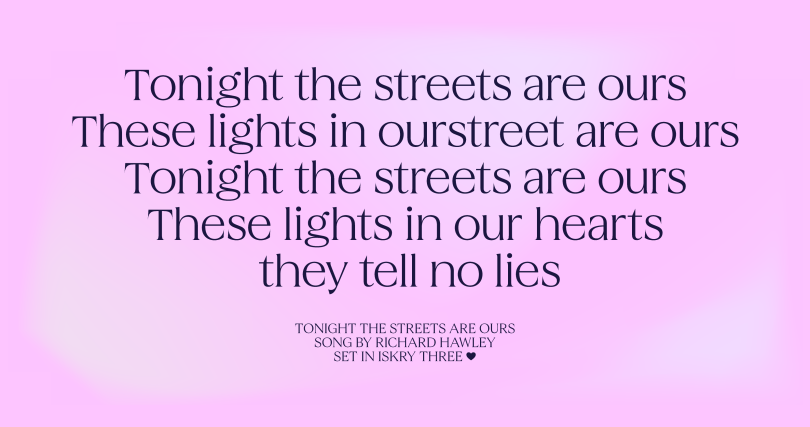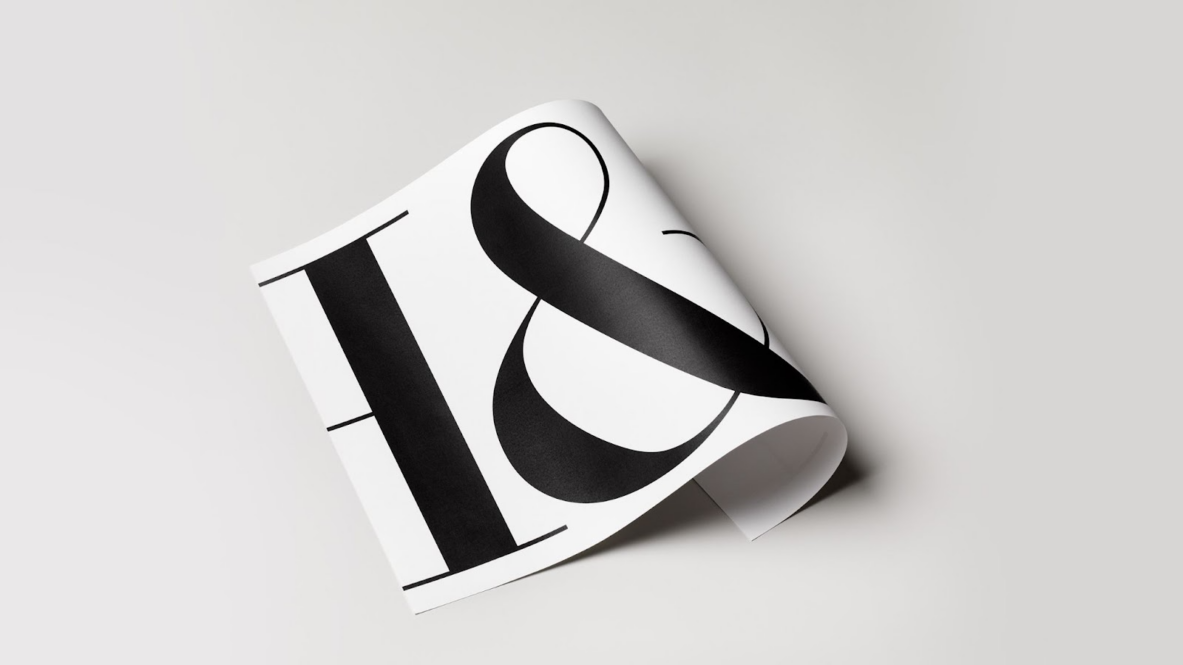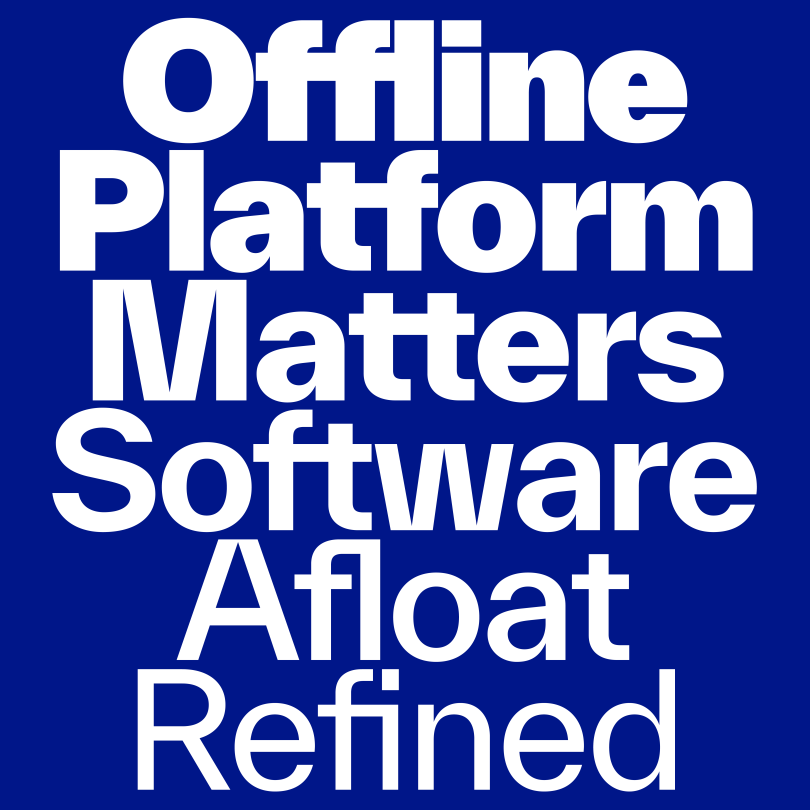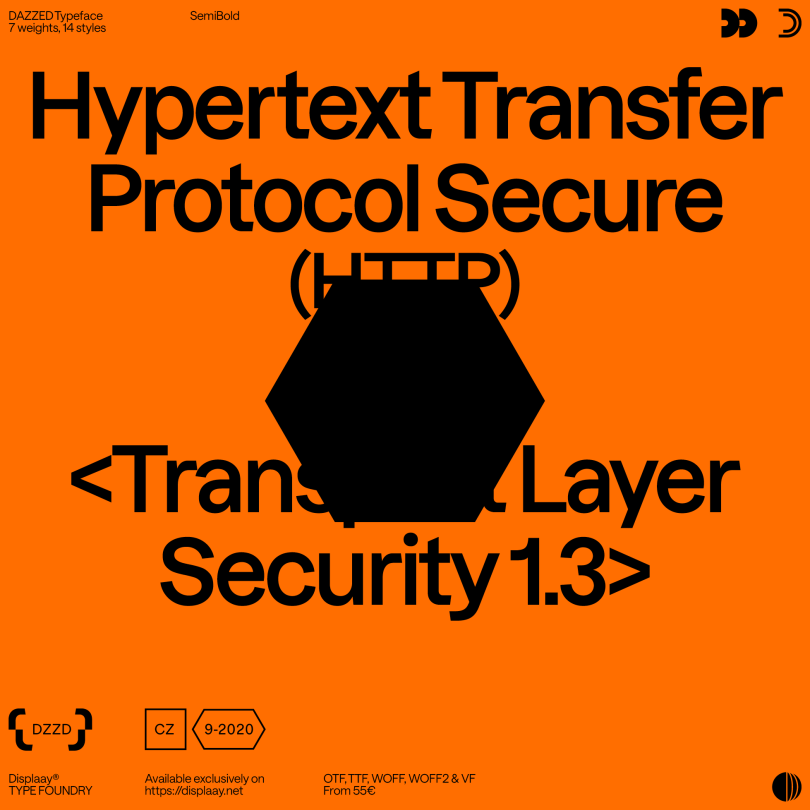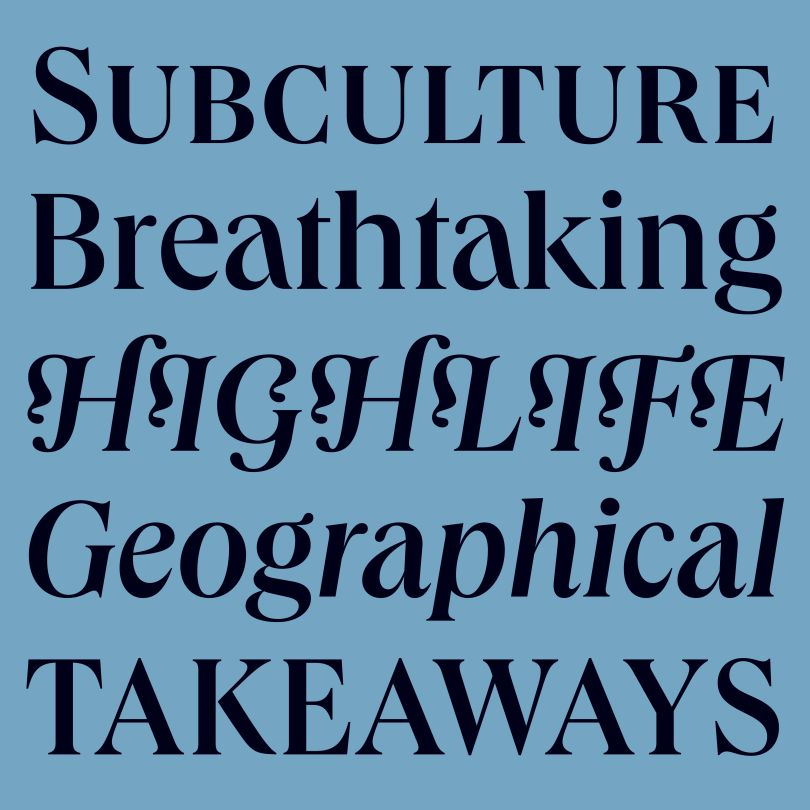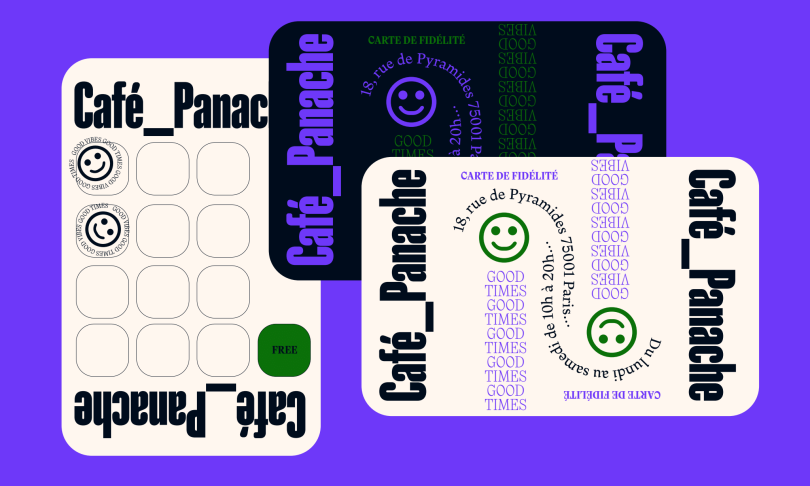
Lựa chọn font chữ thiết kế cho dự án vừa như niềm vui, vừa như nỗi ám ảnh lớn của mỗi Designer. Làm sao để cân bằng yếu tố thương mại và font cách cá nhân luôn là dấu hỏi khó tìm lời giải. Trong bài viết dưới đây, hãy cùng Arena Multimedia khám phá 14 gợi ý kiểu chữ giúp Designer giải tỏa nỗi lo này nhé!
Tương tự tình yêu, cảm xúc của nhà thiết kế dành cho các font chữ đôi lúc thoáng qua, nhẹ nhàng nhưng cũng đầy mãnh liệt và đam mê. Mặt khác, mỗi Designer đều mong muốn trải qua năm tháng ổn định cùng một kiểu chữ chắc chắn, đáng tin cậy, có thể hỗ trợ và đồng hành xuyên suốt các dự án trong khoảng thời gian theo đuổi thiết kế.
14 font chữ thiết kế đáp ứng mọi “jobs” của Designer (Phần 1)
Dưới đây là danh sách 14 font chữ thiết kế giúp Designer tạo nên sự kết hợp hoàn hảo cho đời sống thiết kế của riêng mình, đáp ứng mọi cung bậc cảm xúc và mục đích cụ thể của nhà thiết kế. Tất nhiên, giữa vô vàn kiểu chữ sẽ không tránh khỏi lựa chọn chủ quan, nhưng dù bạn không thật sự yêu thích thì đây vẫn là những kiểu chữ được phát triển bởi đội ngũ studio và Designer xuất sắc từ khắp nơi trên thế giới, rất đáng để bạn cân nhắc.
1. Irregardless của Ohno Type
Irregardless là kiểu chữ sans-serif do James Edmondson của công ty Ohno Type thiết kế, sở hữu giao diện tươi mới, dễ nhìn và vô cùng độc đáo. Về quá trình ra đời của kiểu chữ này, chính James cũng cảm thấy mơ hồ: “Một vài dự án có con đường phát triển rõ ràng nhưng Irregardless thì hoàn toàn trái ngược. Tôi không biết ý tưởng về kiểu chữ bắt nguồn từ đâu, và trong phần lớn thời gian nghiên cứu về Irregardless, tôi vẫn không chắc chắn dự án sẽ tiến triển đến đâu. Đây giống như một sự rèn luyện để tôi chống lại sự bốc đồng của bản thân, xây dựng thói quen để có thể sáng tạo những điều mới mẻ và không thoải mái.”
Được phát hành vào tháng 5/2021, font chữ thiết kế này là một trong số nhiều kiểu chữ vui nhộn và mang tính nguyên bản của Ohno Type mà James đã ra mắt vào năm 2018. Cùng với việc sáng tạo font chữ, công ty cam kết đưa Ohno trở thành một cái tên ảnh hưởng tích cực trong cộng đồng Graphic Design và Typography Design. Để thực hiện hóa mục tiêu này, họ sẽ tiến hành những buổi đối thoại, chia sẻ cùng sinh viên, hoặc đưa ra lời nhận xét, góp ý và các nội dung giáo dục miễn phí.
2. NaN Tragedy của NaN
NaN Tragedy là một font chữ gốc được tạo ra bởi JB Morizot từ NaN theo định dạng văn bản, chữ nghiêng và kiểu chữ hiển thị. Cấu trúc và nguồn năng lượng NaN Tragedy của hướng đến sự đối lập cùng tồn tại bên trong một thực thể: “Cổ điển nhưng vẫn mang tính đương đại. Độc đáo nhưng vẫn có tính tiện dụng. Năng động, font khoáng nhưng vẫn chắc chắn. Lộng lẫy nhưng rõ ràng và đơn giản.”
NaN Tragedy Text kết hợp các chức năng của kiểu chữ văn bản với hình dáng độc đáo, sử dụng hiệu chỉnh quang học để hiện thị tính năng. Chẳng hạn như font cách hướng nghiêng của ký tự và độ tương phản dày mỏng từ kiểu chữ thư pháp. Trong khi đó, thiết kế của font chữ NaN Tragedy Display mang tính nhỏ gọn và chặt chẽ hơn, góp phần nhấn mạnh sự đặc sắc cho những dòng thiết kế tiêu đề.
Phát hành lần đầu tiên vào năm 2019, đây là một trong nhiều kiểu chữ tuyệt vời được thiết kế bởi NaN, studio chuyên về Graphic Design và Typeface Design tại Berlin và Sydney. Đội ngũ studio cho biết: “Cùng hệ thống cộng tác viên, đội nhóm và khách hàng tuyệt vời của chúng tôi, chúng tôi khám phá tất cả mối liên quan giữa code và công nghệ nhằm phục vụ cho các mục đích cụ thể của từng dự án.”
3. Everett của TYPE.WELTKERN
Everett là một kiểu chữ sans-serif sở hữu thiết kế tối giản. Cấu trúc đối xứng của Everett được tạo nên bởi sự kết hợp giữa nét vẽ truyền thống và các yếu tố kỹ thuật. Những chi tiết mạnh mẽ trong kiểu chữ tạo nên tính tập trung cao độ nhưng vẫn đảm bảo sự thoải mái cho việc đọc, cân bằng hài hòa bởi tính đồ họa và mục tiêu gây sự chú ý, thu hút đối với người xem.
Sự phối hợp giữa ascenders (phần chữ nằm trên đường cơ sở) và descender (đoạn kéo dài bên dưới đường cơ sở) cho phép người thiết kế sắp đặt văn bản với khoảng cách dòng chặt chẽ, tiết kiệm không gian. Các font chữ được trang bị những phong cách khác nhau, bao gồm cả chữ ghép, phân biệt chữ hoa và chữ thường cùng nhiều tính năng hơn nữa. Sự thay đổi độ dày mỏng từ Hairline đến Super với chữ in nghiêng tương ứng, tạo thành tính nhất quán và linh hoạt, phù hợp là font chữ thiết kế dành cho thiết kế sách, poster, bộ nhận diện thương hiệu, hệ thống biển báo, v.v…
Ban đầu, kiểu chữ Everett xuất hiện từ năm 2015, khi Nolan Paparelli vẫn còn trong quá trình học tập tại ECAL (Đại học Nghệ thuật và Thiết kế Lausanne, Thụy Sĩ). Theo đó, Nolan được truyền cảm hứng từ tác phẩm của nhiép ảnh gia người Mỹ – Daniel Everett. Khi Nolan phát triển kiểu chữ này, nó nhanh chóng in đậm dấu ấn cá nhân và trở thành phong cách riêng của nhà thiết kế với thể loại nghệ thuật bí ẩn, kỳ lạ (Grotesque).
Everett chính thức xuất xưởng vào tháng 3/2021, là một trong những kiểu chữ cao cấp do TYPE.WELTKERN, công ty thiết kế kiểu chữ của Thụy Sĩ thành lập vào năm 2021 bởi Nizar Kazan. Mục tiêu chính của TYPE.WELTKERN hướng đến việc tôn vinh đội ngũ nhà sáng tạo làm ra các kiểu chữ, chia sẻ doanh thu từ đối tượng, sách hoặc font chữ thiết kế mà họ sản xuất và xuất bản. Công ty tự hào rằng nhà thiết kế của họ đạt được phần trăm doanh số tốt hơn so với mức trung bình thị trường.
4. Font chữ thiết kế Rainer của Vectro Type
Rainer thuộc kiểu chữ sans-serif hình học, sở hữu kiểu dáng thời thượng và hiện đại, phù hợp cho những tiêu đề chặt chẽ hoặc bất cứ đối tượng nào cần đến định dạng big type để tạo điểm nhấn và gợi tâm trạng cho người xem. Rainer được nén với khẩu độ đón, chiều cao font chữ khá lớn, phần ascenders (chữ nằm trên đường cơ sở) ngắn và descender (đoạn kéo dài bên dưới đường cơ sở) còn ngắn hơn. Rainer bao gồm 12 font cách cùng 6 mức độ đậm nhạt khác nhau (từ Hairline đến Bold) ở dạng thẳng, nghiêng và đi kèm một số hỗ trợ ngôn ngữ mở rộng, cũng như tất cả thể loại hình dạng mũi tên và ký tự được chọn lựa một cách cẩn thận.
14 font chữ thiết kế đáp ứng mọi “jobs” của Designer (Phần 1)
Ảnh: creativeboom.com
Font chữ thiết kế Rainer do Philipp Neumeyer thiết kế và được phát hành bởi Vectro Type – studio lĩnh vực Typeface Design có trụ sở tại thành phố Portland, tiểu bang Oregon, Hoa Kỳ, chuyên thiết kế kiểu chữ theo yêu cầu, các dịch vụ sản xuất font chữ, v.v… Thành lập vào năm 2015 bởi bộ đôi Travis Kochel và Lizy Gershenzon, studio nổi tiếng với việc khám phá điểm giao thoa giữa công nghệ, sự hữu ích và nét vui tươi trong thiết kế kiểu chữ.
5. Iskry của Laic
Iskry là kiểu chữ serif với những ký tự độc đáo và kỳ quặc, chứa đựng sự tương phản mạnh mẽ, sắc nét và rực rỡ, vô cùng thích hợp cho mục đích hiển thị trên màn hình hoặc sử dụng trong các ấn phẩm in ấn. Trục chữ cái của kiểu chữ vô cùng đa dạng kết hợp cùng chiều lớn, phù hợp để ứng dụng cho thiết kế tiêu đề.
14 font chữ thiết kế đáp ứng mọi “jobs” của Designer (Phần 1)
Ảnh: creativeboom.com
Font chữ thiết kế Iskry ra đời vào tháng 1/2020 bởi Laic – một studio thiết kế đồ họa có trụ sở tại Warsaw, Ba Lan chuyên về thiết kế kiểu chữ và các tác phẩm nghệ thuật bằng con chữ. “Iskry” trong tiếng Ba Lan có nghĩa là “tia lửa”, studio giải thích: “Tia lửa là thứ gì đó rất nhỏ, có thể đột ngột phát ra một sự ấm áp hoặc ánh sáng nhưng cũng có thể là những mảnh nhỏ của chất liệu phát sáng.”
6. Queen của Kilotype
Queen được xuất bản lần đầu tiên vào năm 2019, là một kiểu chữ hiển thị với lối thiết kế cổ điển và thanh lịch, lấy cảm hứng từ thiết kế của Bodonis & Didots. Tuy nhiên, điểm khác biệt của Queen nằm ở việc lược bỏ những cấu trúc có phần cứng nhắc và tập trung hướng đến sự tươi vui trong thiết kế. Font chữ thiết kế Queen nhận được nhiều điểm cộng nhờ việc tích hợp một loạt tính năng và sự phức tạp của kiểu chữ.
14 font chữ thiết kế đáp ứng mọi “jobs” của Designer (Phần 1)
Ảnh: creativeboom.com
Queen sở hữu 3 độ rộng (Compressed, Condensed và Standard), được thiết kế với ý tưởng chủ đạo về sự đa dạng và kỳ quặc, đồng thời những tiêu chuẩn liên quan đến nhịp điệu trong thiết kế cần phá vỡ để có thể phát triển hơn nữa. Kiểu chữ thống nhất chữ “a” sẽ nghiêng về phía sau với các hướng nhấn nét xen kẽ của chữ “e” và “o”. Trong khi đó, chữ “t” nằm trên đường cơ sở, hoán đổi phần đuôi truyền thống bằng một kiểu chữ có chân. Đồng thời, các phần loe ra bên ngoài cũng được gọt giũa, tạo thành chữ “f” in nghiêng tương phản với phần cuối tương tự hình giọt nước.
Queen được sáng tạo bởi Kilotype – một xưởng đúc chữ của Đức thành lập vào năm 2017, hứa hẹn hỗ trợ nhiều ngôn ngữ cũng như sở hữu tiêu chuẩn sản xuất chất lượng cao đối với mọi kiểu chữ. Bên cạnh hệ thống danh mục kiểu chữ của riêng họ, Kilotype còn phát triển giải pháp tùy chỉnh dành cho khách hàng thương mại và các tổ chức.
7. Font chữ thiết kế Dazzed của Displaay
Dazzed là một kiểu chữ sans-serif tỷ lệ hẹp và được sử dụng đầu tiên cho mục đích điện ảnh, dung hợp một số phong cách trong một font chữ. Phát hành lần đầu vào tháng 7/2019, kiểu chữ gợi lên sự hài hước, kỳ quặc và kịch tích, thể hiện qua các chữ “a”, “e”, “c” và “g”. Đồng thời, Dazzed còn mang đến cảm giác hành động, khoa học viễn tưởng trong thiết kế của chữ “t”, “f”, “r”. Đặc biệt, phần đầu cuối bị cắt bỏ một phần, tương phản với những dạng chữ cổ điển khác. Các dấu chấm được thiết kế theo dạng hình tròn, giúp người đọc dễ dàng nhận dạng hơn, cũng như hệ thống chữ in nghiêng 18° với các mức độ thấp hơn vẫn có sẵn theo yêu cầu.
14 font chữ thiết kế đáp ứng mọi “jobs” của Designer (Phần 1)
Ảnh: creativeboom.com
Dazzed do studio Displaay phát triển, đây là địa chỉ chuyên về thiết kế đồ họa và thiết kế kiểu chữ, được thành lập vào năm 2016 và có trụ sở tại Praha, Cộng Hòa Séc. Lấy cảm hứng từ những khoảnh khắc không hoàn hảo, Displaay tập trung vào bán lẻ và các font chữ thiết kế tùy chỉnh, đồng thời phát triển những kiểu chữ đặc biệt, hiếm thấy trên thị trường.
Xem thêm: 26 công cụ làm việc tốt nhất dành cho dân thiết kế (Phần 2)
Nguồn tham khảo: creativeboom.com
Diệu Ngô
Chương trình đào tạo Mỹ thuật Đa phương tiện (Arena Multimedia Specialist Program – AMSP) đào tạo Chuyên gia Mỹ thuật Đa phương tiện trong 2,5 năm. Với tính chất bao quát mọi lĩnh vực của ngành công nghiệp sáng tạo và giải trí, AMSP là cánh cửa mở ra các cơ hội nghề nghiệp đa dạng: Thiết kế Đồ họa, Thiết kế Web, Làm phim; Thiết kế Game, Hoạt hình 3D. Đặc biệt, học viên Arena đều được “va chạm” với các công việc trong ngành ngay từ năm nhất nhờ các cơ hội thực tập và việc làm từ mạng lưới doanh nghiệp, đối tác rộng lớn.